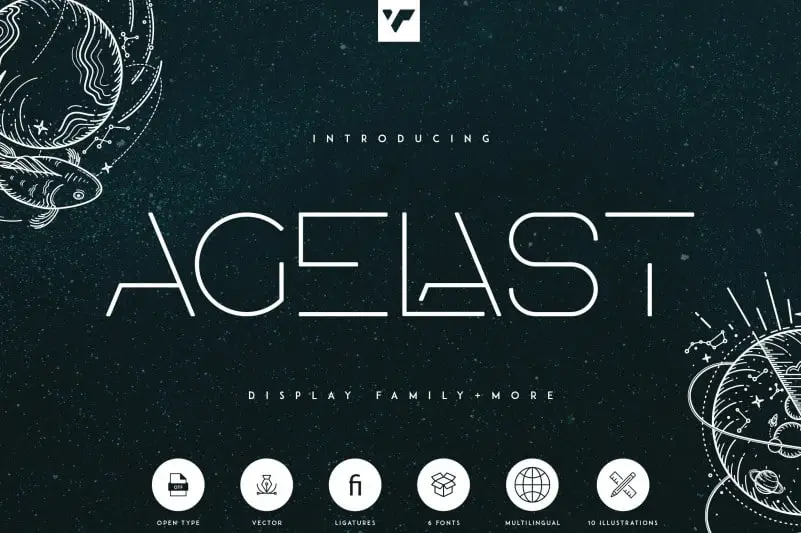
A Agelast Display Font Family oferece uma nova maneira de estilizar seu design com 10 ilustrações incríveis e 71 temas Photoshop para aprimorar sua identidade visual digital. Desenvolvida pela equipe proeminente do vp_creative_shop, esta fonte é perfeita para designers que desejam dar um toque único em seus projetos. Com sua ampla gama de estilos e ilustrações únicas, a Agelast permite ao designer criar uma identidade visual vibrante, tornando seu trabalho mais atraente e memorável. Este conjunto de fontes é perfeito para aquelas iniciativas que buscam manter um tom moderno e sofisticado em suas campanhas digitais, sem perder o detalhe e o charme. Com apenas uma dessas belas fontes, você pode dar ao seu design um toque definitivo.